万万没想到繁花的字体设计灵感来源鲁迅的字体设计
“繁花”这两个字的灵感来源不是别的,正是我们的设计老前辈——鲁迅先生,是他所创作的《萌芽月刊》。
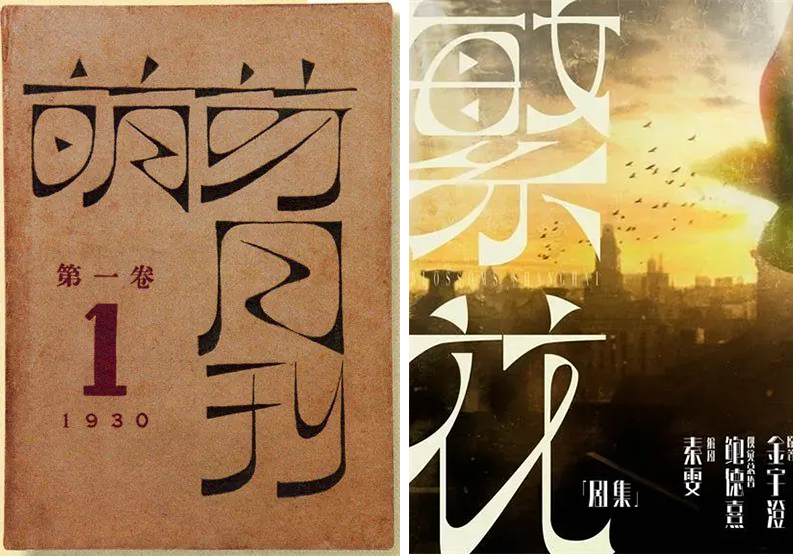
细看“萌芽月刊”与“繁花”,无论是字体的特征还是个性,我们都能看到鲁迅老先生所设计的字体的影子。
新时代字体再创作——【萌芽体】
2022年7月2日,方正字库联合北京服装学院艺术设计学院视觉传达设计专业的黄秋实同学设计,依照《萌芽月刊》的封面四个字的字体结构为母本,通过分析其中的汉字笔画特征。总结归纳出其中的规律,并进一步延伸出更多的笔画和部件,依照结体特点设计出更多字体,总结归纳提炼设计成【萌芽体】,以致敬鲁迅,链接时代精神。
下图为【萌芽体】字体的研究过程以及应用的示范样张,字体过小的时候灰度不是特别均匀,因此这款字更多地适应于标题、海报等场合。
除了字体设计本身,黄秋实还用“萌芽体”设计了一系列的书籍封面。
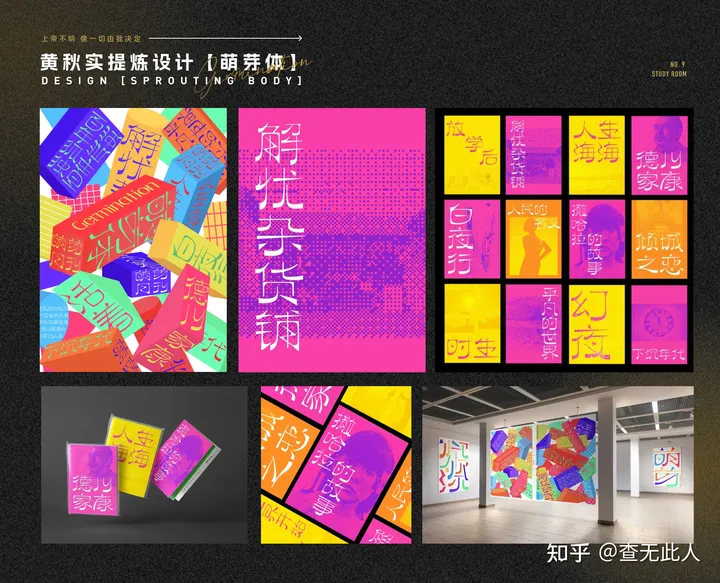
另外,还得提到一款开源字体————逐浪还有一款萌芽字体,与之很相似,切免费开源可商用。其字体设计来源萌芽月刊;
关于逐浪萌芽体
字体效果
创作理念
一款参照借鉴近代中国共产党《萌芽》月刊的艺术字体。
源自五四运动文化,力求体现近代文艺风。
字体线条呈现外方内圆格局,有尖锐的外角、三角部件,而内部空间则呈现圆形切割效果。
这体现了五四、清末民初,在工业革命思维冲击下,一代文化人对于中国汉字的探索。
又似布尔什维克人的工人、工业文化在汉字下的体现。
尖锐、锐角三角形的部件,从中体现了上进、革命、进击。
结字扁形,即左右宽度大于上下高度。
- 1.外角采用尖角,内角采用弧角
- 2.是一个抽象的孤形字。
- 3.试图创造上个世纪30年代“左联”的手写字体风格,该风格是用于出版物出版,简朴又不失艺术性。
- 4.多弧形、多三角形。
- 5.整体偏矮宽方正型,非常规字体,异型字居多
- 6.笔画粗细对比明显,角的笔画相对横竖线要粗
- 7.竖线笔画下端粗上端细,横线笔画左边粗右边细
- 8.外角整体偏方形,内角整体偏圆形的创意字体
- 9.整体风格硬朗纤细
创作笔记